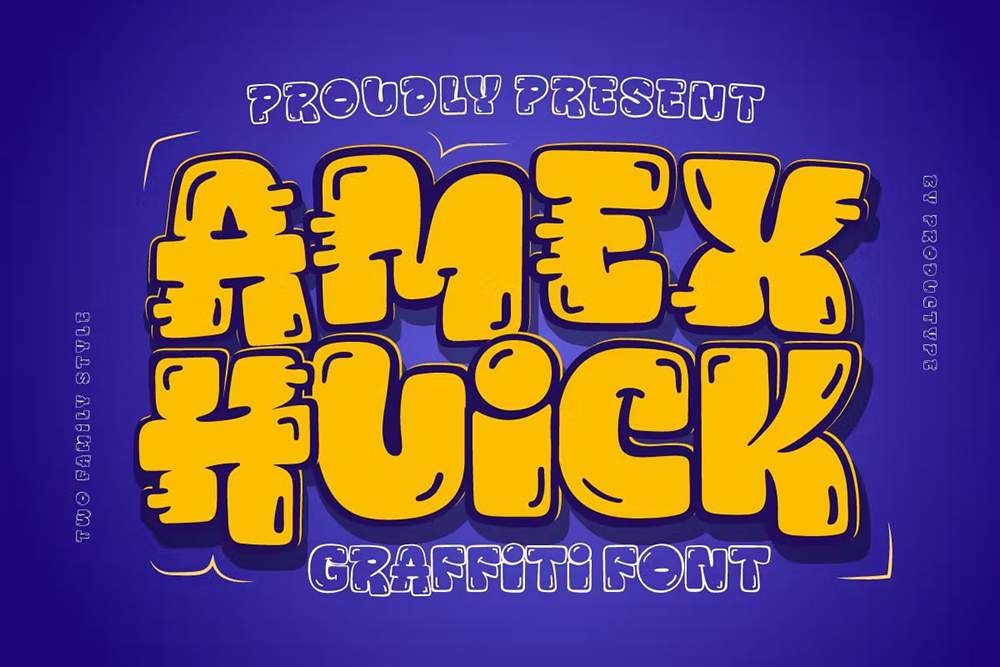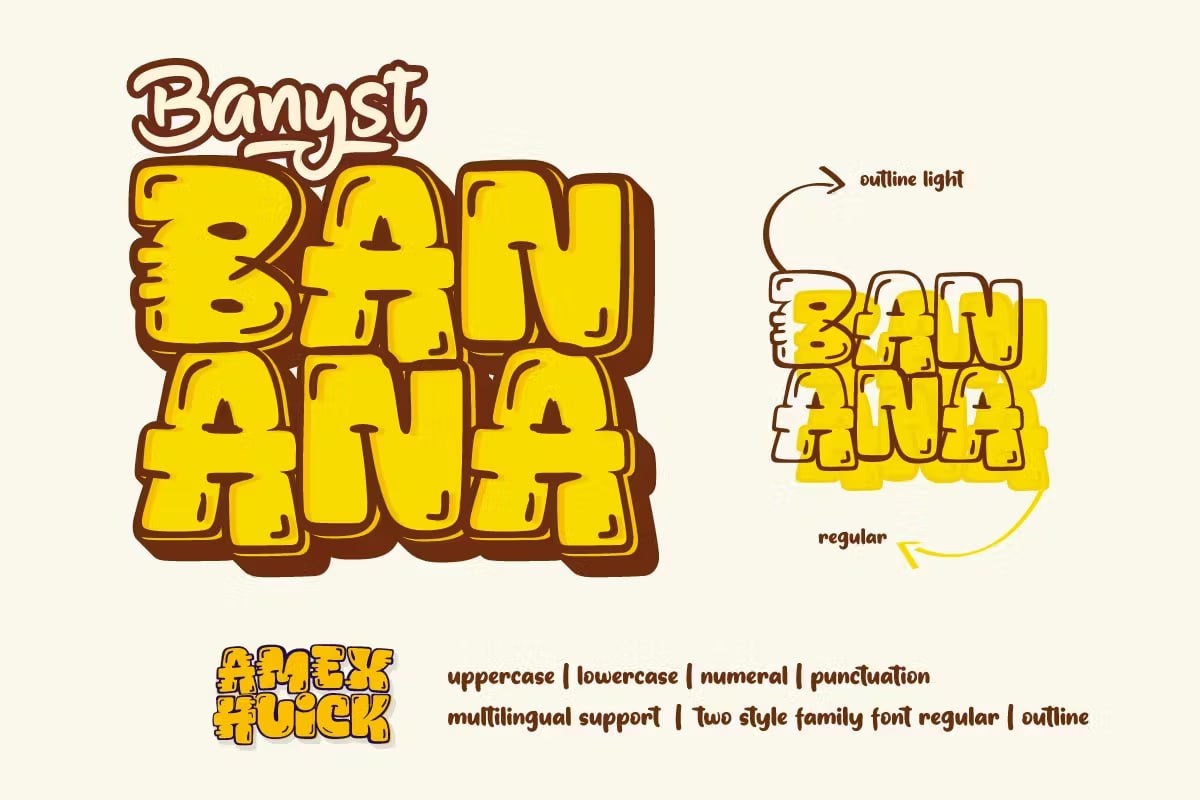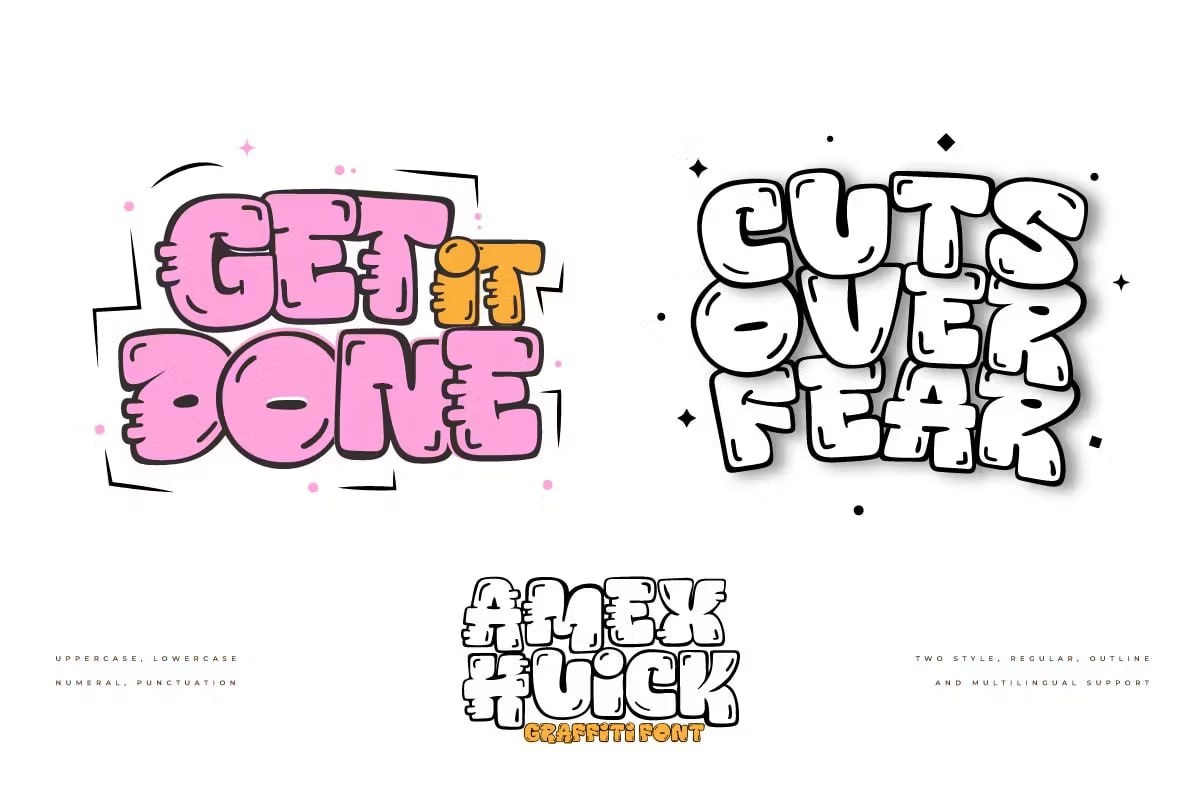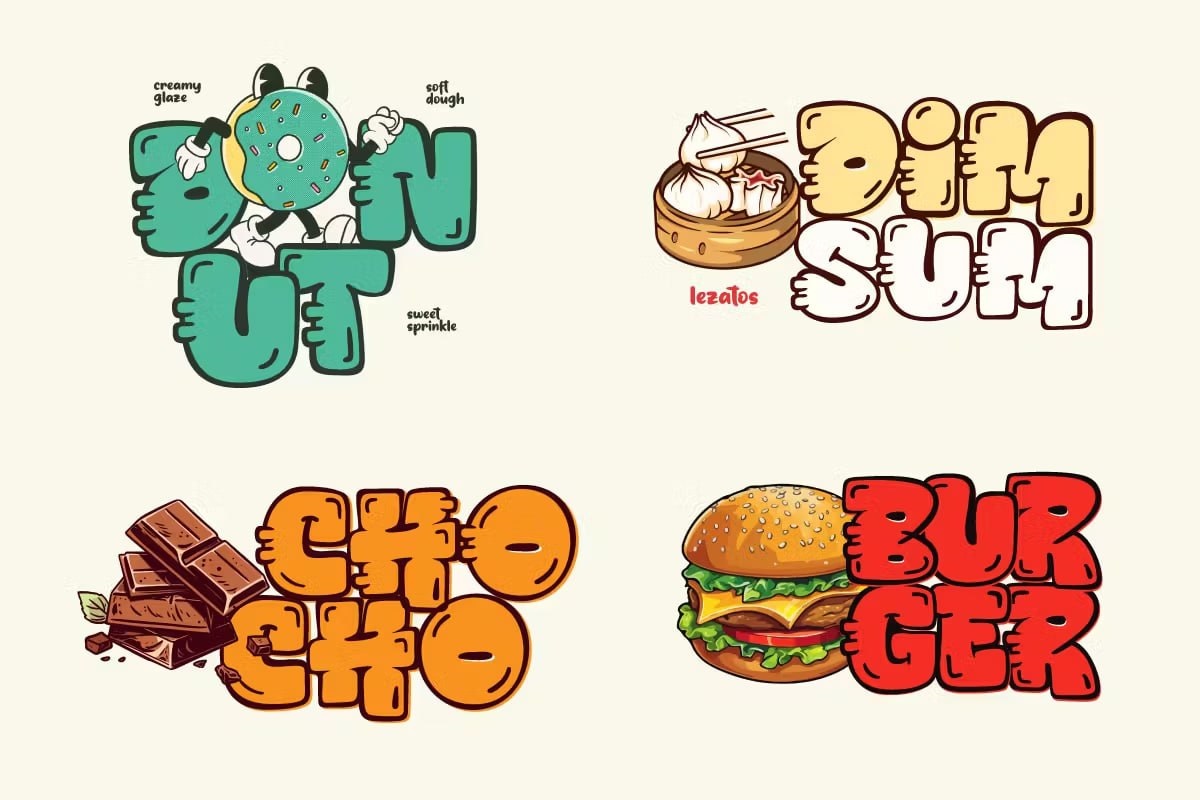
فونت پرمیوم و انگلیسی AMEX HUICK Font یک فونت گرافیتی پویا در دو سبک می باشد. AMEX HUICK برای طراحی های هنری خیابانی، برندسازی، پوسترهای شهری و…
فونت پرمیوم و انگلیسی AMEX HUICK Font یک فونت گرافیتی پویا در دو سبک می باشد. AMEX HUICK برای طراحی های هنری خیابانی، برندسازی، پوسترهای شهری و موارد دیگر ایده آل است. اين فونت برای هر پروژه برندسازی مانند لوگو و… مناسب است.